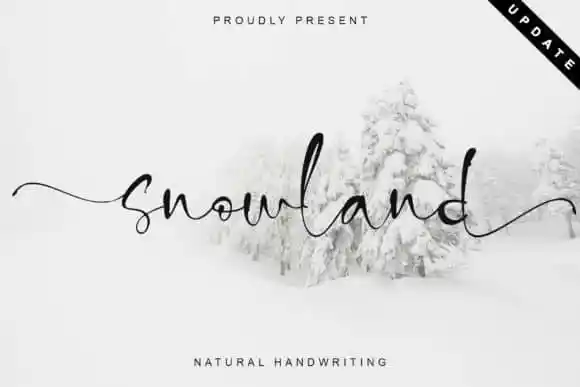
Snowland Script Font – Fonte Grátis
Snowland Script Font
A fonte Snowland Script é uma criação artesanal, cheia de vida e beleza natural. Inspirada em uma escrita manuscrita orgânica, ela é perfeita para dar um toque único aos projetos digitais. Esta font foi desenhada por Thomasaradea através do site 99designs, mantendo-se fiel às influências chamigas de cera ao mesmo tempo que mantém uma presença contemporânea e fresca. A Snowland Script é PUA encoded, o que significa que você pode acessar facilmente todos os caracteres e alternativas estilizadas. Seus traços são suaves e variam no baseline, oferecendo um charme único para qualquer projeto impresso ou digital. Os caracteres também têm ares elegantes, mas ao mesmo tempo modernos e vivos. É perfeita para quem está procurando algo que dará vida e graça a qualquer projeto de design gráfico em que seja aplicada, trazendo seu trabalho aos melhores níveis.